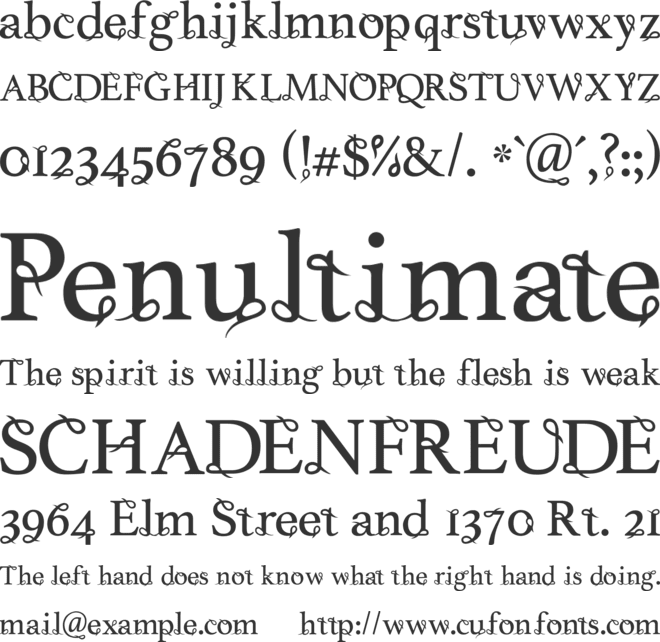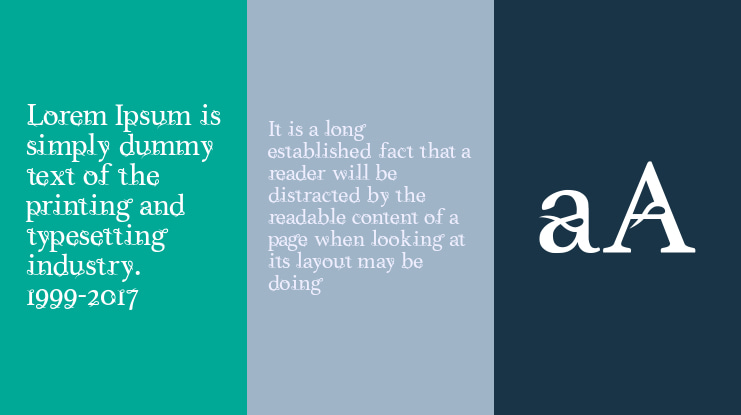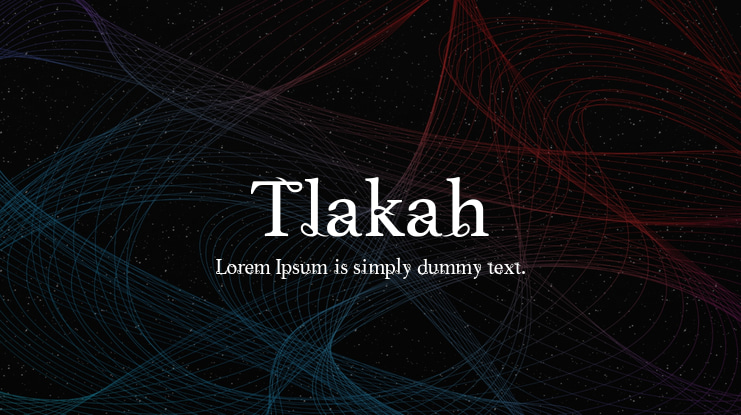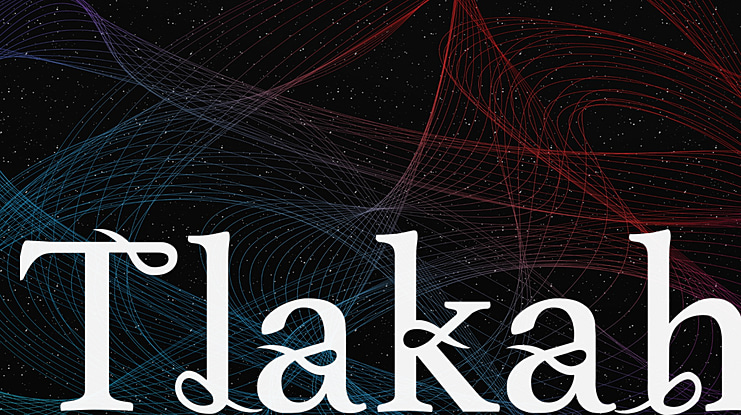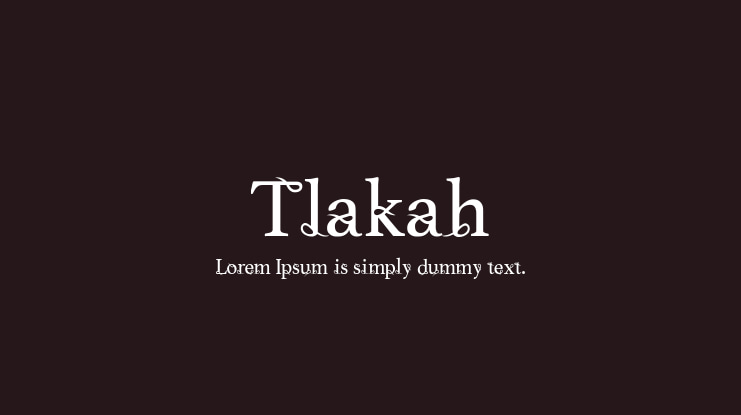
Tlakah Font
Galia Atri
Esta tipografía esta inspirada en la cultura nahuatl, por lo que el nombre tlakah significa gente en la lengua de esta cultura, así mismo cuenta con signos especiales de la cultura que se siguen utilizando hoy en día.